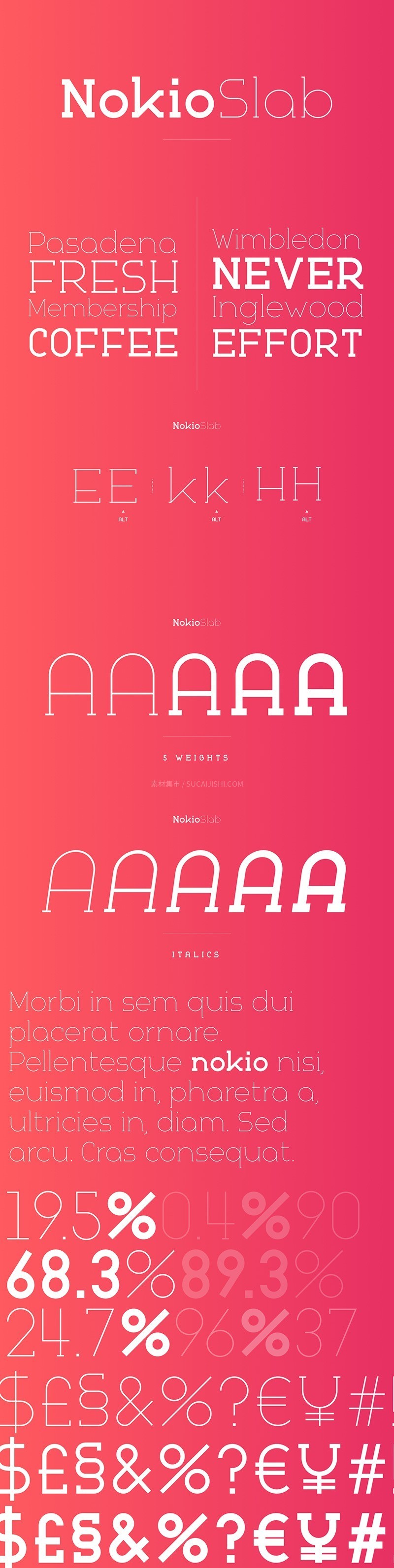
Nokio系列全套英文字体
Nokio 字体凭借其巧妙融合的简洁线条和曲线,以及结构清晰、略带俏皮感的独特气质,成为一款广受欢迎的字体。Nokio 系列包含三种风格变体,根据您的项目需求,灵活选用,展现不同的视觉效果。
Nokio 以简洁的线条和曲线搭配流畅圆润的字尾
Nokio系列全套英文字体
Nokio Slab 时尚感十足的衬线字体
Nokio系列全套英文字体
Nokio Sans 简洁、极简主义的无衬线字体
Nokio系列全套英文字体